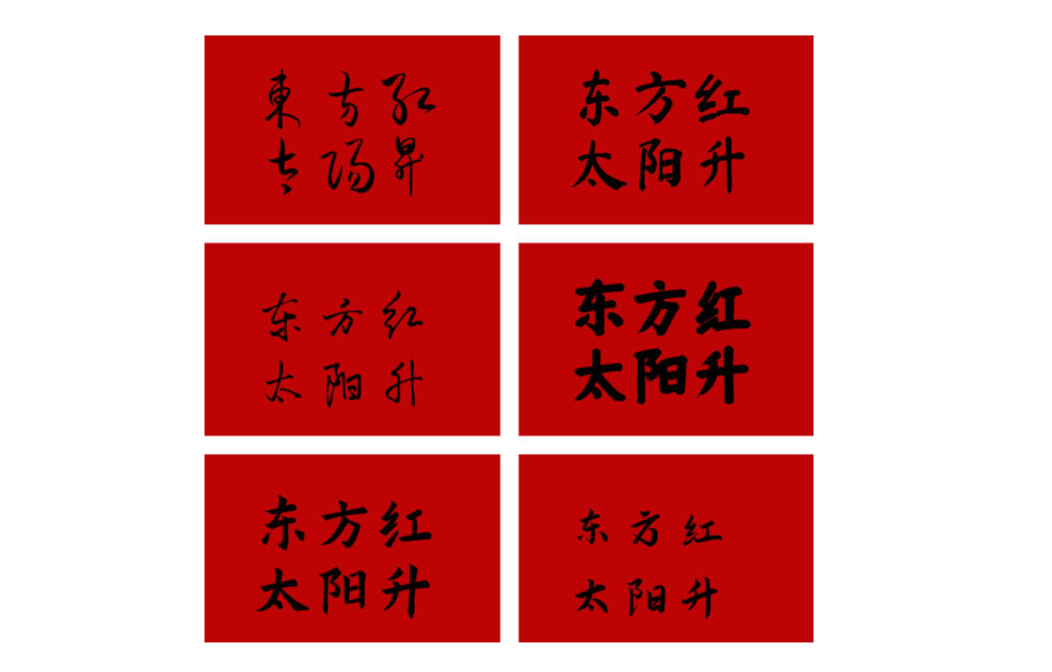
本套设计素材包含18款书法字体,专为Procreate用户及国潮风格设计项目开发。字体融合传统书法韵味与现代设计理念,适用于包装设计、品牌LOGO、标题排版等场景,可有效提升作品的艺术表现力与文化内涵。
核心优势:
1;风格多元:提供18种不同表现力的书法字体,覆盖多样设计需求
2;国潮适配:传统书法笔触结合现代设计语言,完美契合国潮项目
设计建议:
适用场景:传统文化元素需求强烈的包装设计/品牌标识/标题排版等
组合技巧:建议与其他字体或设计元素搭配,增强视觉层次感